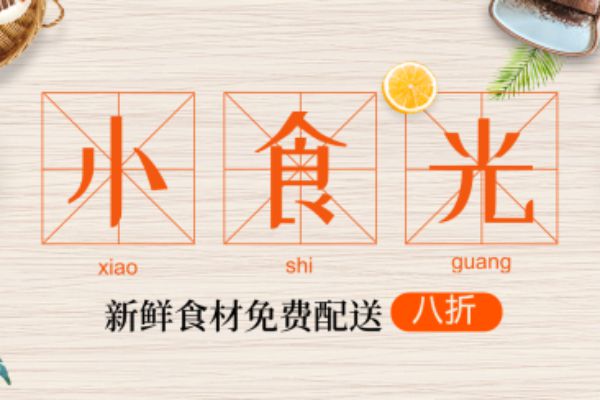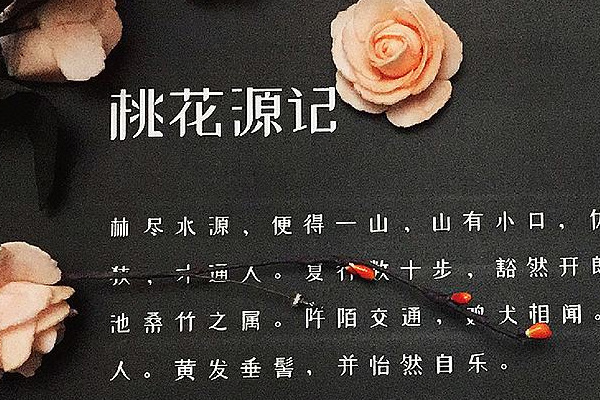
字体下载 站酷小薇LOGO体
站酷小薇LOGO体
由上海佐兹品牌设计工作室设计总监李大卫 (David 小马哥)带领其工作室团队共成完成。【站酷小薇LOGO体】是李大卫送给自己女儿出生三周年的一个礼物。其目的是为了填补免费字体中的LOGO体空缺。字体笔画浑厚,识别性高,放大放小空间间隙都能如意灵通。采用GB2312汉字编码,共收录6763个汉字。